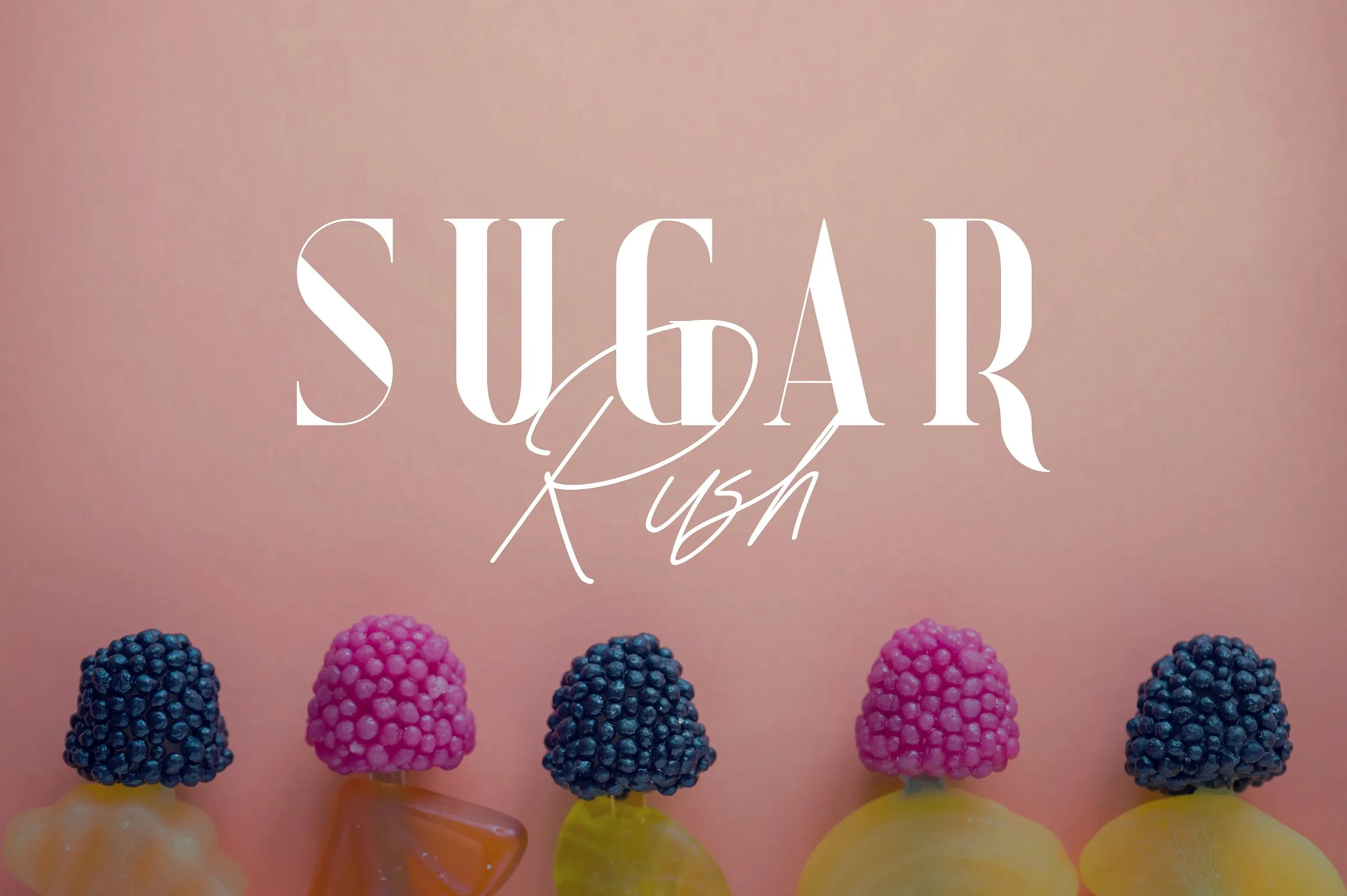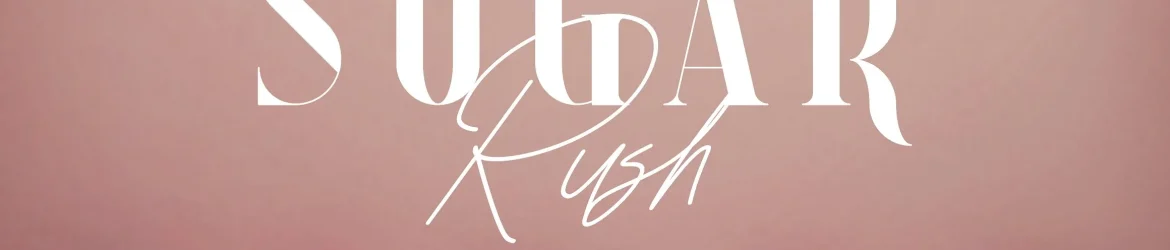
Sugar Spice é uma paleta elegante e contemporânea composta por tipografias script e serif. Este par perfeito traz a sofisticação de um tipo serif com um estilo livre e fluido do tipo script, criado pela designer VPcreativeshop. Com o seu fonte serif alto e comprimido que se destaca, combinado à sua companheira script fluída, Sugar Spice oferece uma harmonia moderna entre as duas famílias de tipos. Esta fonte Duo é perfeitamente adaptável para uso em todas as escalas — seja em grandes tamanhos ou design minimalista. Além disso, o Font Duo também vem com 56 elementos gráficos e suporte multilíngue. O Sugar Spice é uma opção versátil que se adapta a vários estilos de design, fazendo dele uma escolha inteligente para qualquer projeto. Seja você um designer ou editor de texto, a elegância e o clareza dos 6 estilos disponíveis garantirão que sua tipografia seja não apenas legível, mas também uma parte encantadora do seu trabalho final.